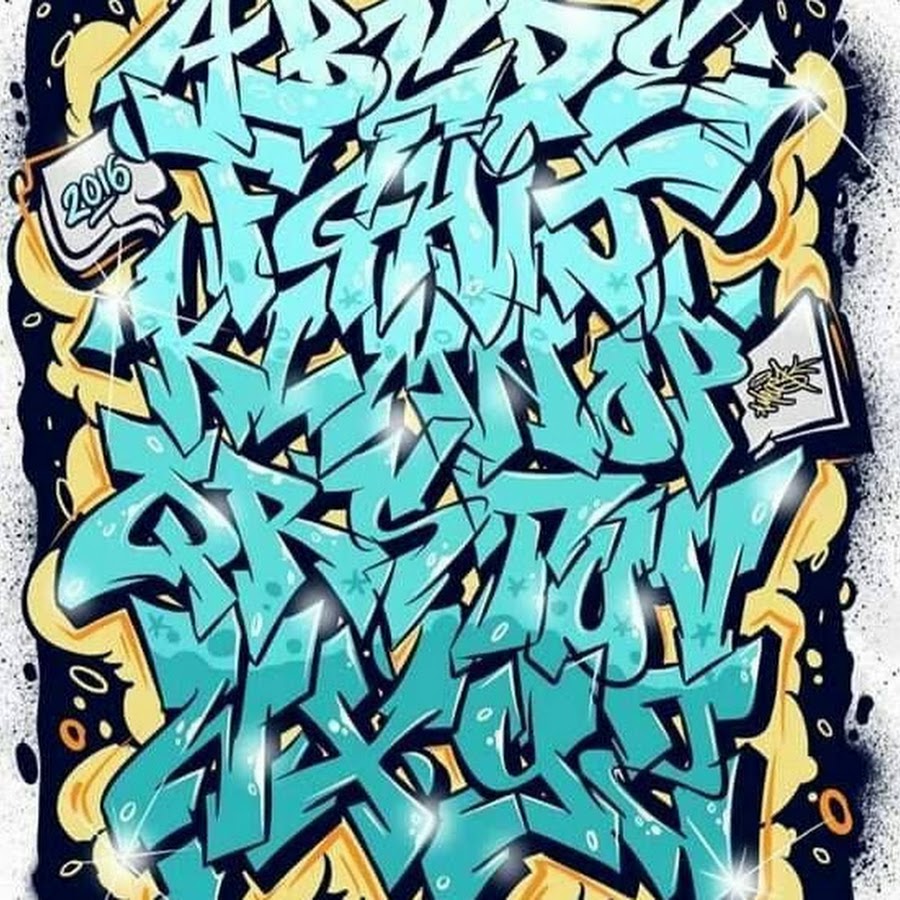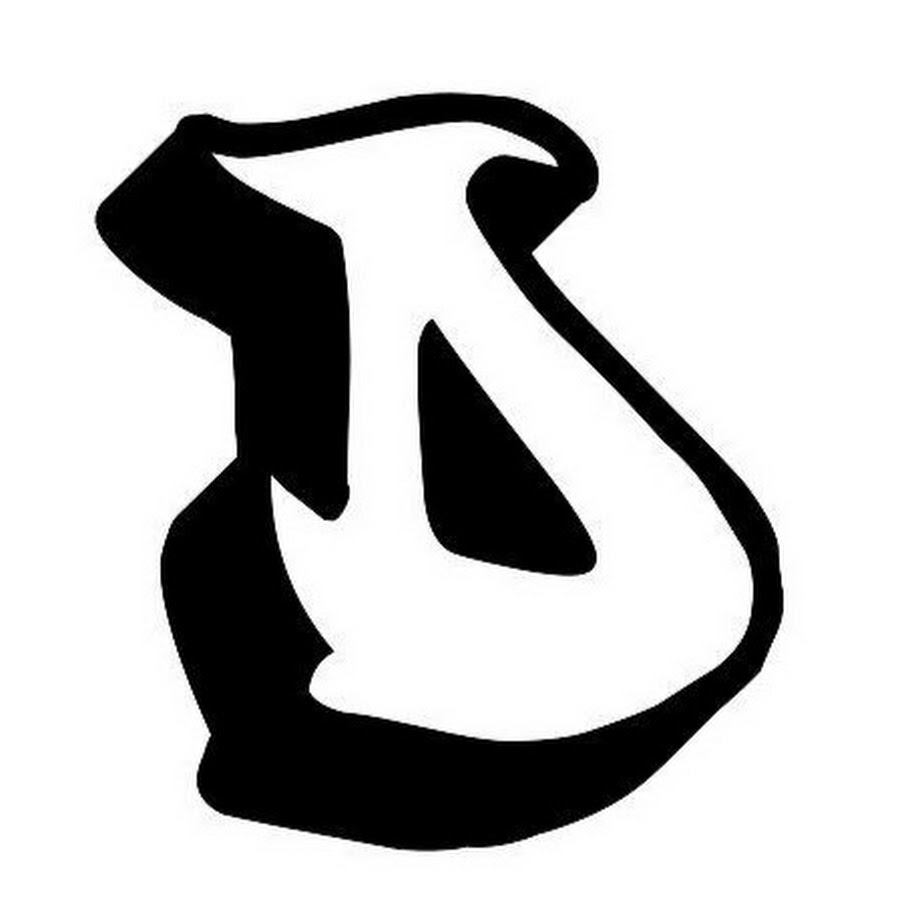
Как рисовать граффити на бумаге для начинающих
Как рисовать граффити на бумаге для начинающих – в этом уроке будем рисовать слово «stop». Такие граффити не отличаются большой сложностью, они рассчитаны на новичков.
Как рисовать граффити на бумаге
Конечно же, можно рисовать более сложные граффити, которые еще будут в других уроках, но для начинающих лучше тренироваться именно на таких, более простых рисунках.
Итак, начнем рисовать граффити на бумаге для начинающих. Рисуем «stop». Начинаю с буквы «О», которая имеет овальную форму и не замкнутые линии.
Далее рисуем букву «t». Нарисовать изогнутые буквы будет, наверное, самой большой сложностью для начинающего.
Опять же, как и в других уроках граффити, я советую вам рисовать буквы сначала простым карандашом, а затем обводить их цветными. Вы всегда сможете стереть простой карандаш, и исправить ошибку. А вот линию цветным карандашом исправить практически невозможно.
После нарисованной буквы «t», рисуем слева первую букву «s». Начало первой буквы изображено в виде стрелки.
Ну и последняя буква, которую следует нарисовать – буква «р». Она состоит из двух частей, обратите внимание. Низ буквы я уже начал разукрашивать карандашом зеленого цвета.
В других уроках, мы обводили черным цветом, а теперь обведем буквы карандашом зеленого цвета. Внимательно посмотрите, как нарисована обводка, и где она утолщается.
Далее карандашом синего цвета светлого оттенка, нужно обвести буквы «р», «t» и «о».
Теперь обводим все буквы карандашом синего цвета оттенком темнее. На рисунке ниже все хорошо видно.
Остается только разукрасить рисунок граффити. Я взял карандаш зеленого цвета, но оттенком светлее, чем обводка. Букву «о» я оставил не закрашенной.
Я надеюсь, у вас получилось нарисовать по этому уроку — как рисовать граффити на бумаге для начинающих. Вы можете пробовать разукрашивать свой рисунок другими цветами, не обязательно следовать в точности как в уроке. То же самое касается и букв, которым можно попробовать изменить наклон или нарисовать их как-то «по-своему».
При помощи клавиши Z можно приближать вид (зумировать) и рисовать более тонкие штрихи и детали. Возможно кому-то этот редактор покажется более интересным ).
Друзья, понравилась ли Вам данная забава? Делитесь своими впечатлениями в комментариях.
Автор статьи: Сергей Сандаков, 40 лет.
Новое прочтение: в России появилась первая граффити-азбука | Статьи
В России продолжается работа над граффити-букварем. Первый вариант «уличной» азбуки уже увидел свет. Автор работы — известный граффити-художник и дизайнер Дмитрий Аске. Всего в ходе проекта российские художники «уличной волны» нарисуют 33 буквы и 33 авторских азбуки.
Как возникла идея
В конце сентября 2019 года на дизайн-заводе «Флакон» прошел мастер-класс по каллиграфии и граффити для подростков, где участники составили композиции из разных шрифтов и расписали стену завода. Тогда же у художников возникла идея создать полноценную азбуку с современным дизайном. Одним из инициаторов был Дмитрий Аске, который ранее участвовал в создании аналогичного букваря немецкой уличной художницы Клаудии Вальде (MadC).
Для кого рисуют новый букварь
Проектом занялись стрит-арт-платформа FGA и развивающий проект для подростков «Кругозор». В создании принимают участие 33 российских граффити-художника, каждый разрабатывает свой вариант азбуки и авторскую букву для нового букваря. За созданием издания можно будет следить онлайн в социальных сетях проекта Кругозор. Так, любой желающий сможет больше узнать об уличной моде, среде стрит-арта и пообщаться с известными художниками в формате онлайн-стримов. А первый вариант буквы и азбуки уже готов.
Если вы посмотрите вокруг своего города, вы увидите повторяющиеся темы в стилях разных художников. Я лично считаю, что писателям полезно поддерживать эти тенденции, поскольку это придает каждому городу свой уникальный вклад в движение.
Если вы делаете граффити с группой друзей, иначе говоря, с командой, вы можете обнаружить, что все вы развиваете похожие стили.